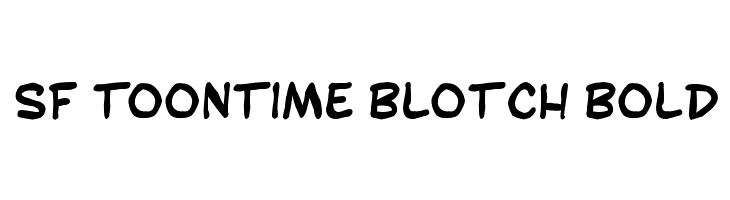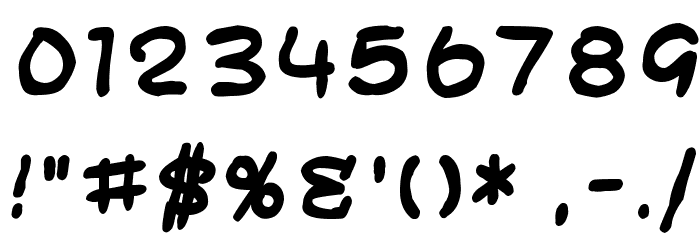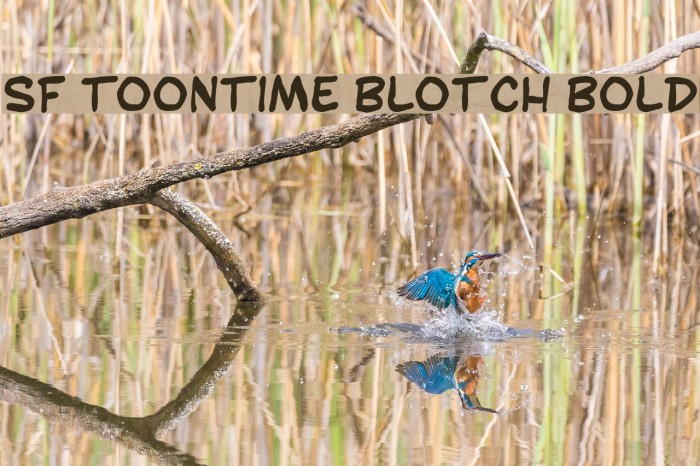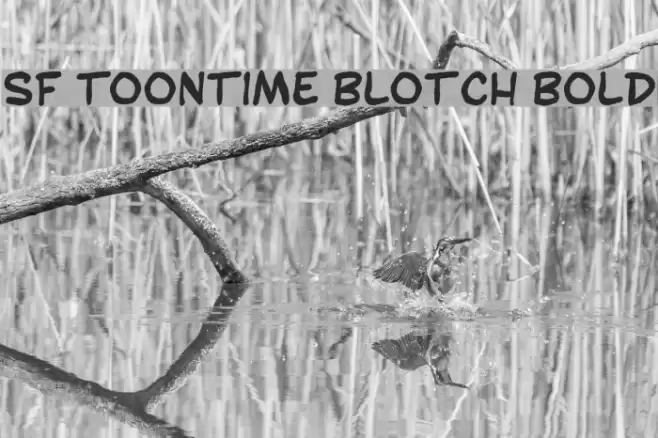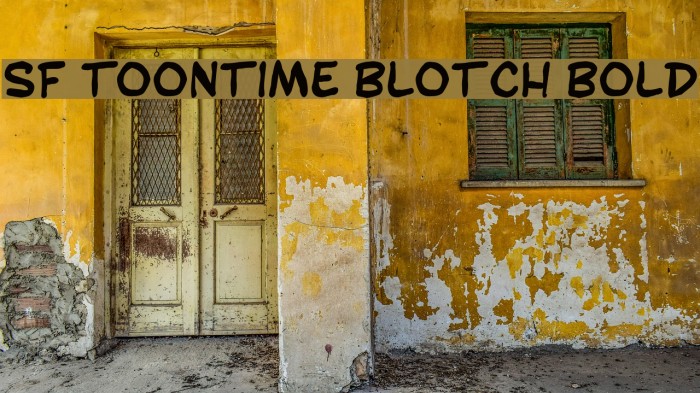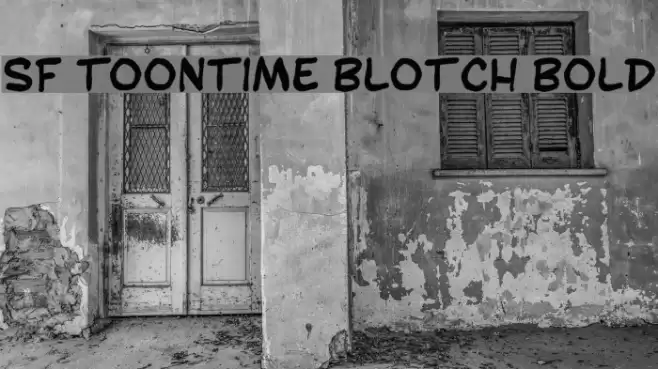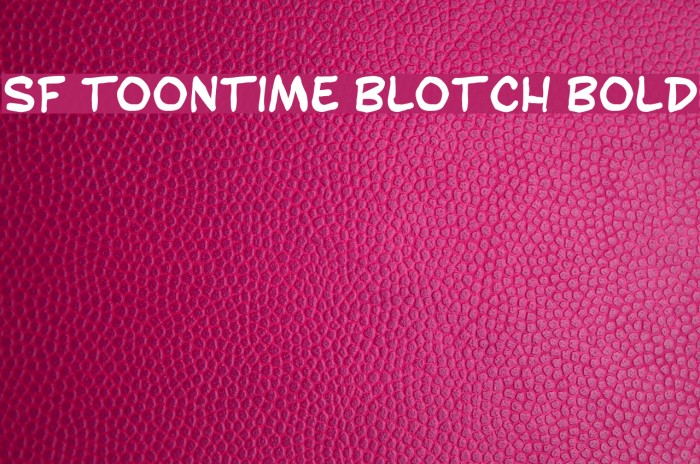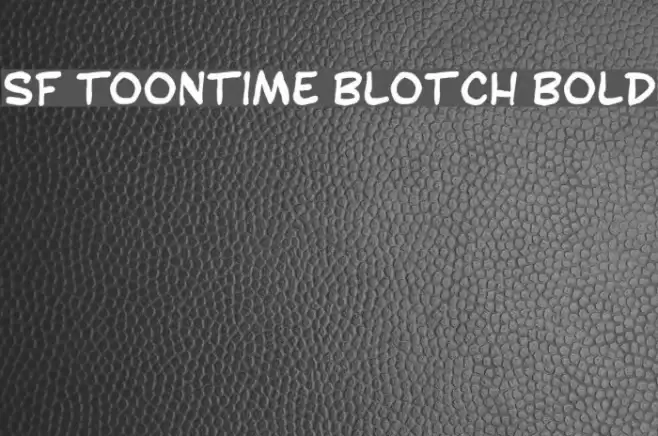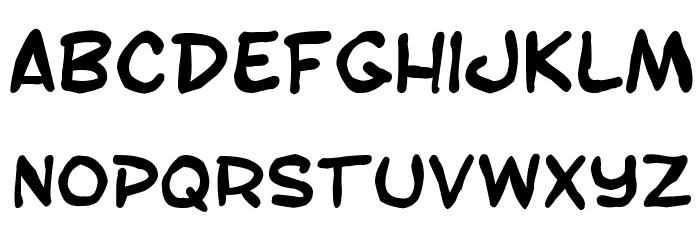
SF Toontime Blotch Bold Font
✎ Comic
| Estilo geral | Playful, Cartoonish |
| Projetos propostos | Ideal for children's books, comic strips, playful branding, and informal event invitations. |